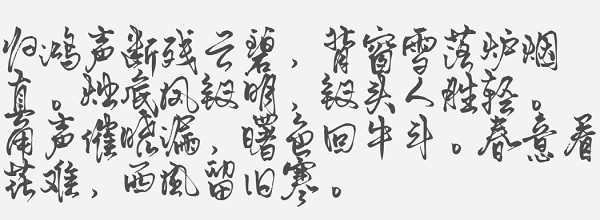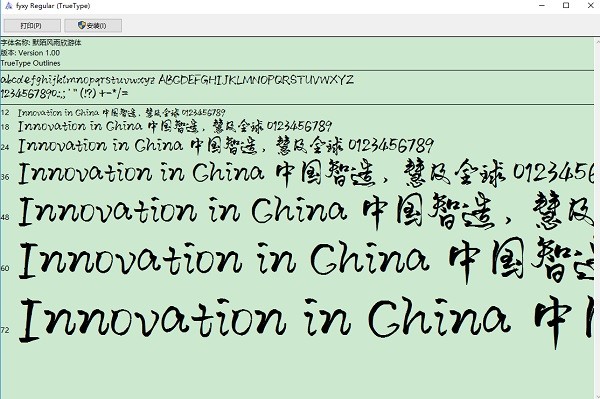
默陌風雨欣游體ttf是非常好看的一種字體,字體整體非常的具有藝術氣息,非常的優(yōu)雅大方,不同于工工整整的字體,此字體略帶一種活潑奔放的感覺,可以廣泛應用于廣告印刷等行業(yè),歡迎大家下載使用!
能夠適用于廣告設計、名片設計、包裝印刷、產(chǎn)品設計等應用
默陌風雨欣游體字形端正大方
非常適合廣告設計、平面設計、印刷包裝、正文標題等人員使用
整體效果十分出眾
應用領域:文字排版、美工設計、海報設計、書籍印刷、報紙周刊、平面設計等方面